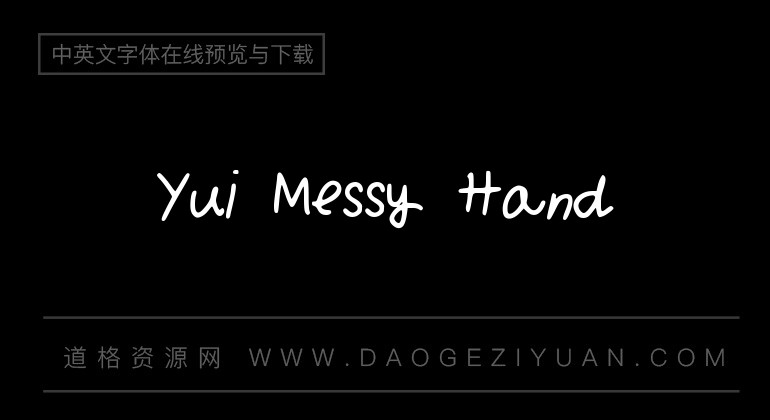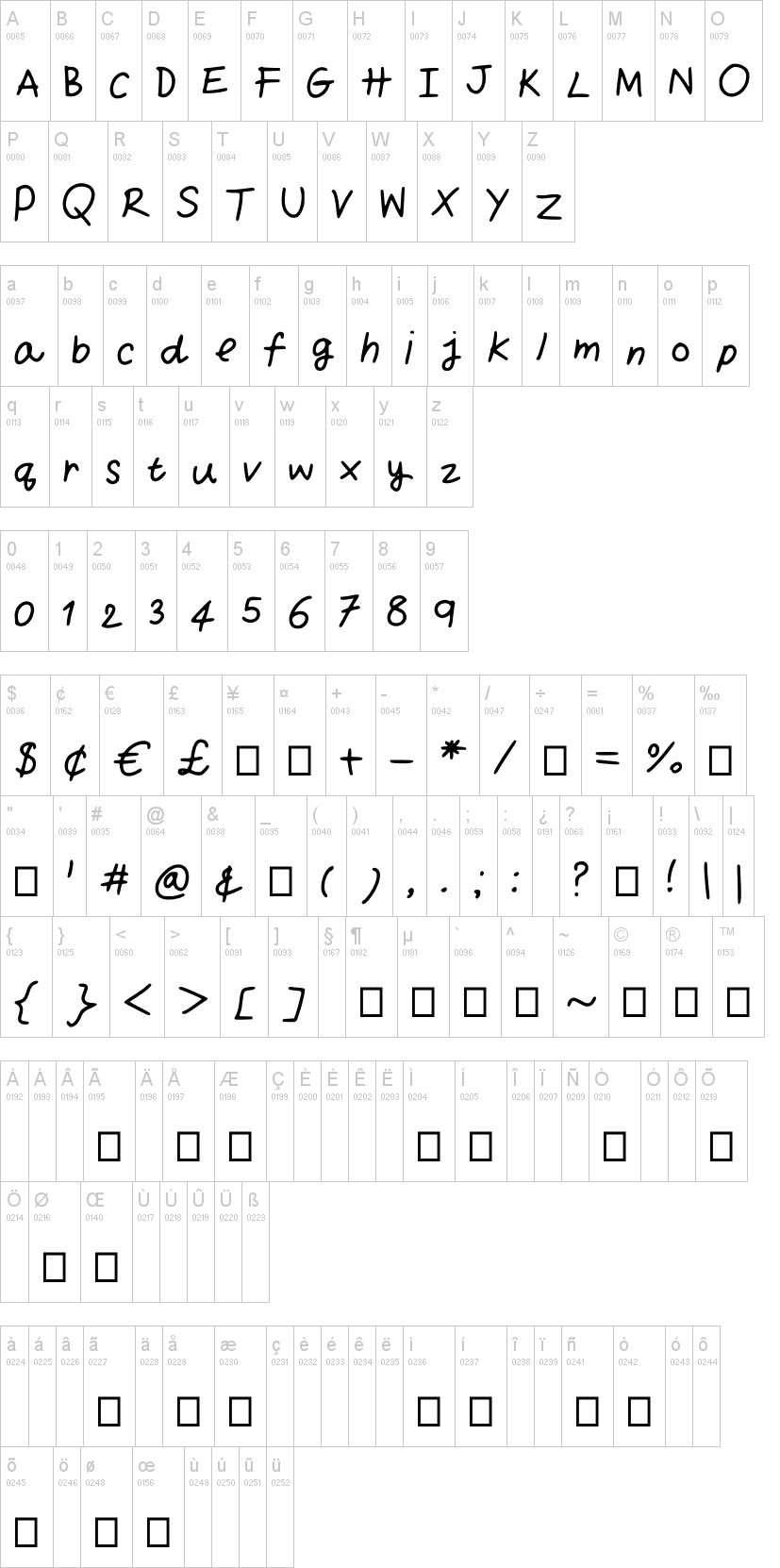
Yui Messy Hand是一款由Yui绘制的手写字体,它拥有清晰的线条,可以提供深入的文本表现力。它拥有独特的设计,可以给你的设计创造出浪漫,温暖的感觉。它具有轻松,活力,时尚,简约的风格,可以用于卡通,漫画,海报,书籍,海报,品牌标志,网页,应用程序等等。它还可以用于创建精美的拼图,故事书,贺卡,婚礼邀请函等。内容介绍
Yui Messy Hand是一款非常不错的手写艺术字体,具有很好的视觉感,适合于文化类的宣传设计、商业类品牌的广告和产品包装设计以及个性化文字排版等较多场景。